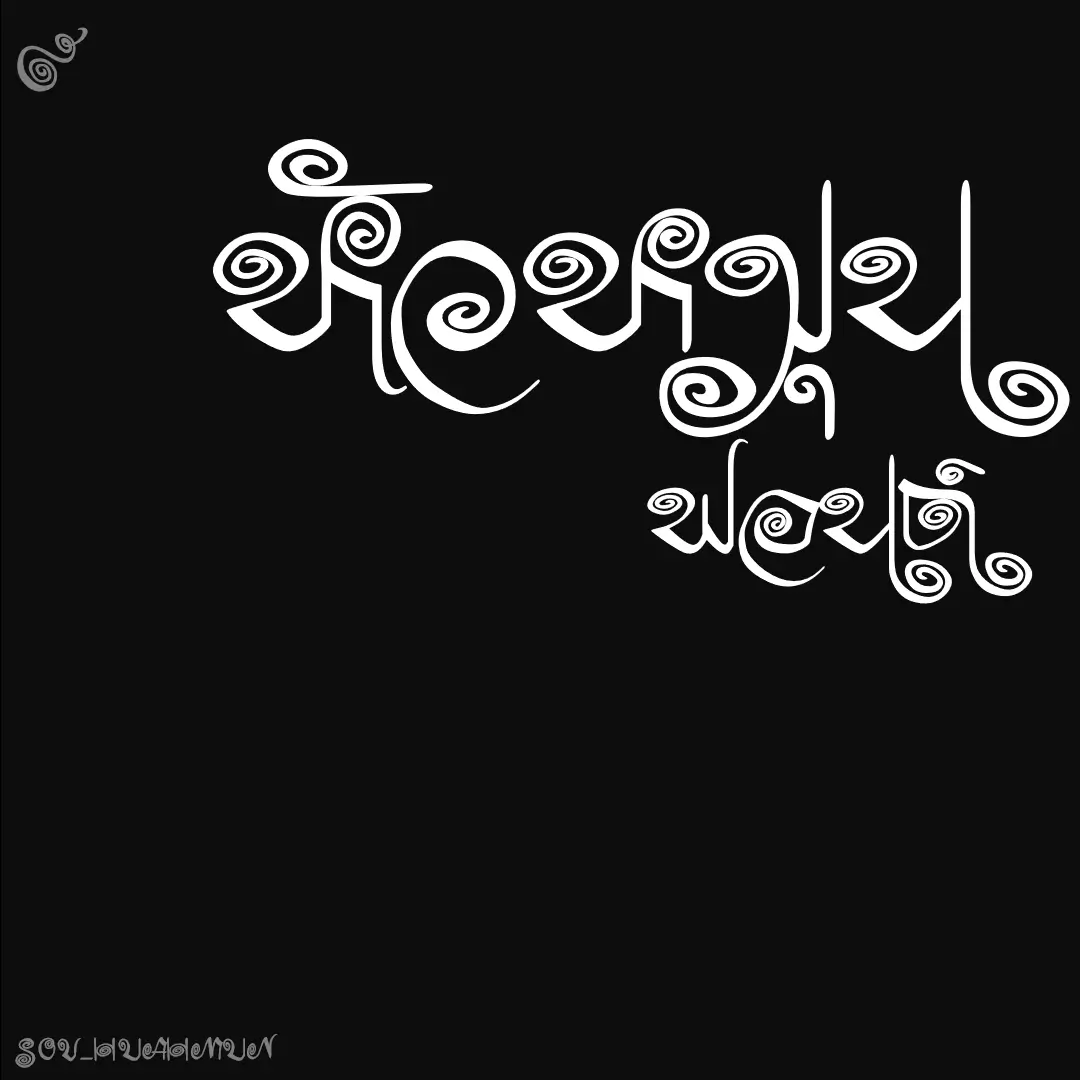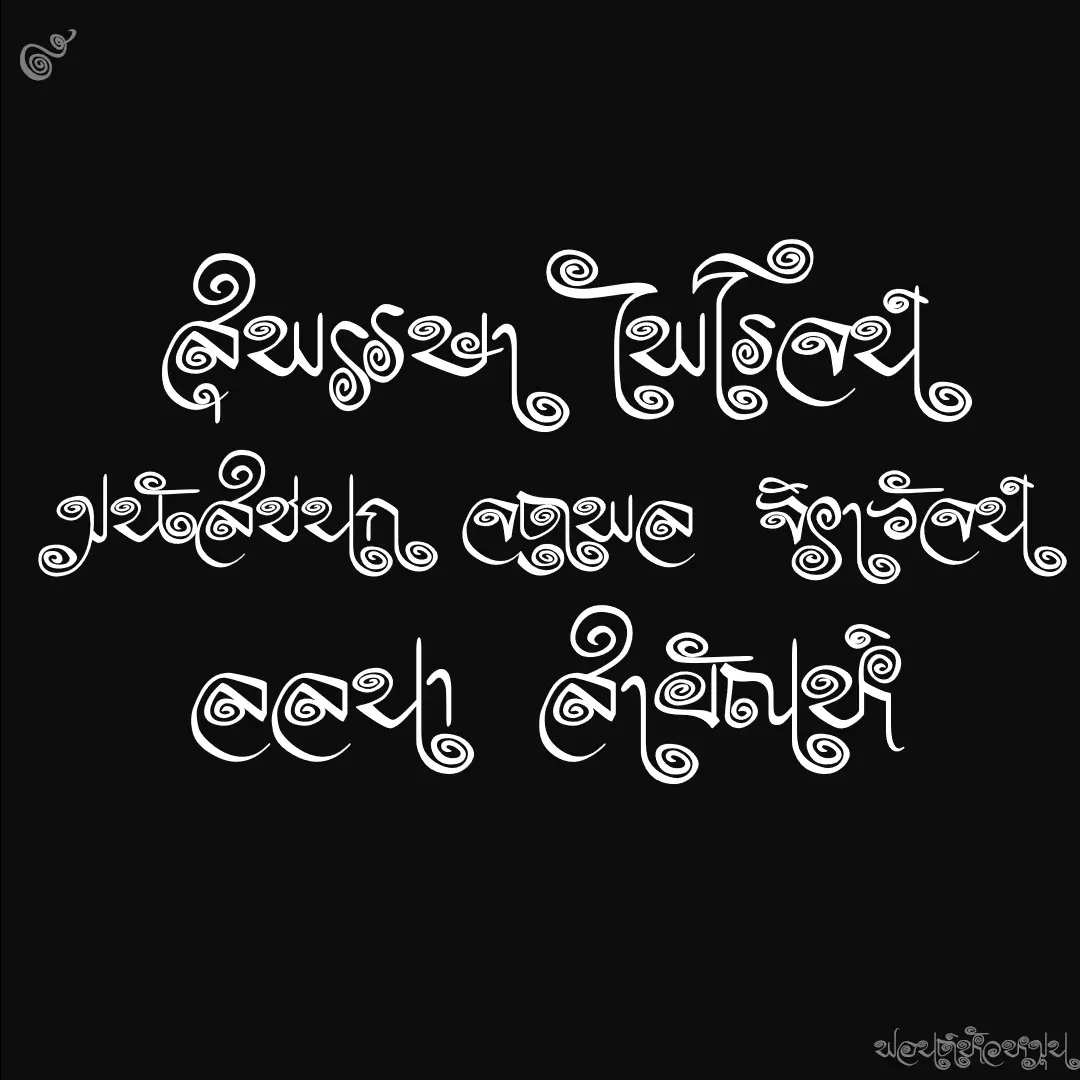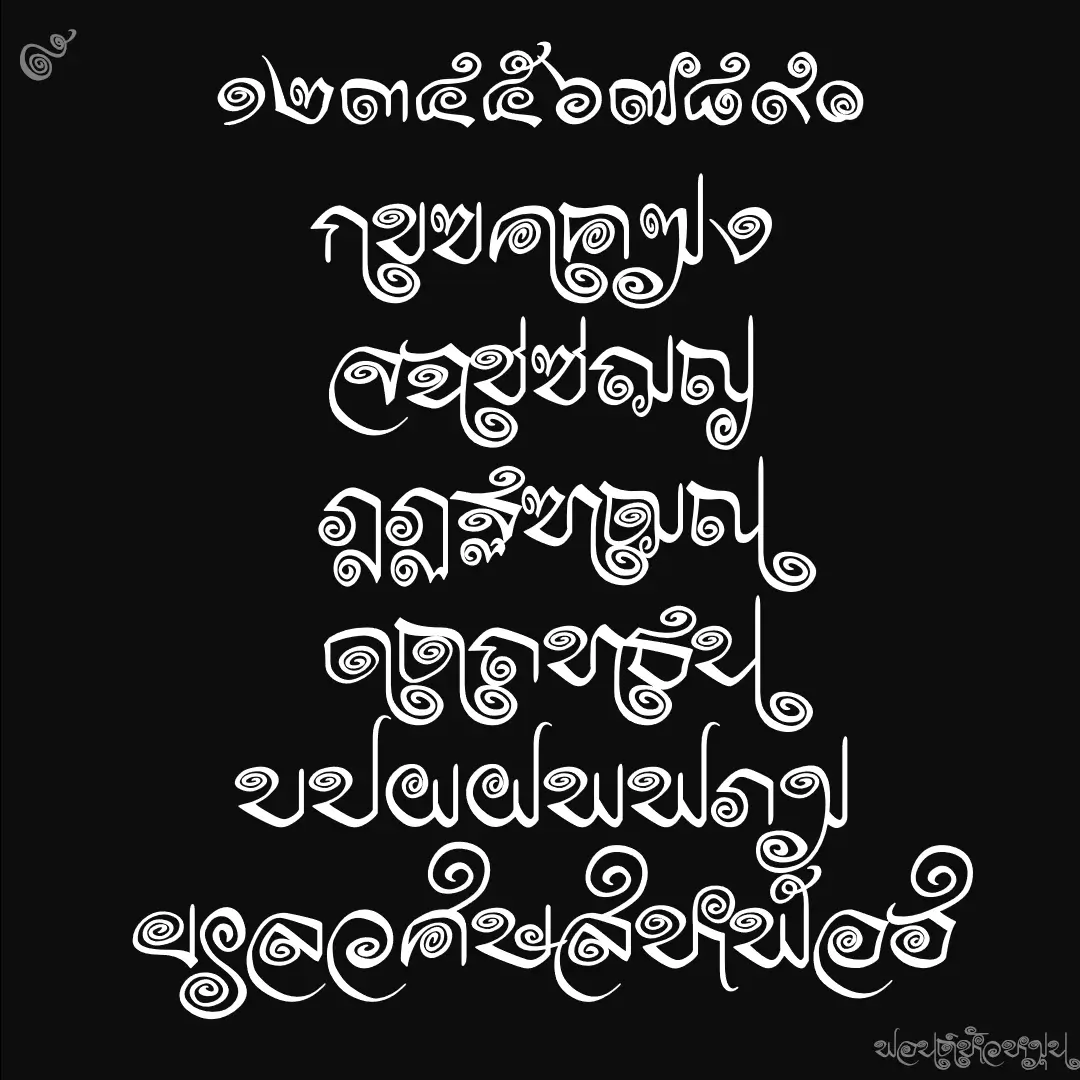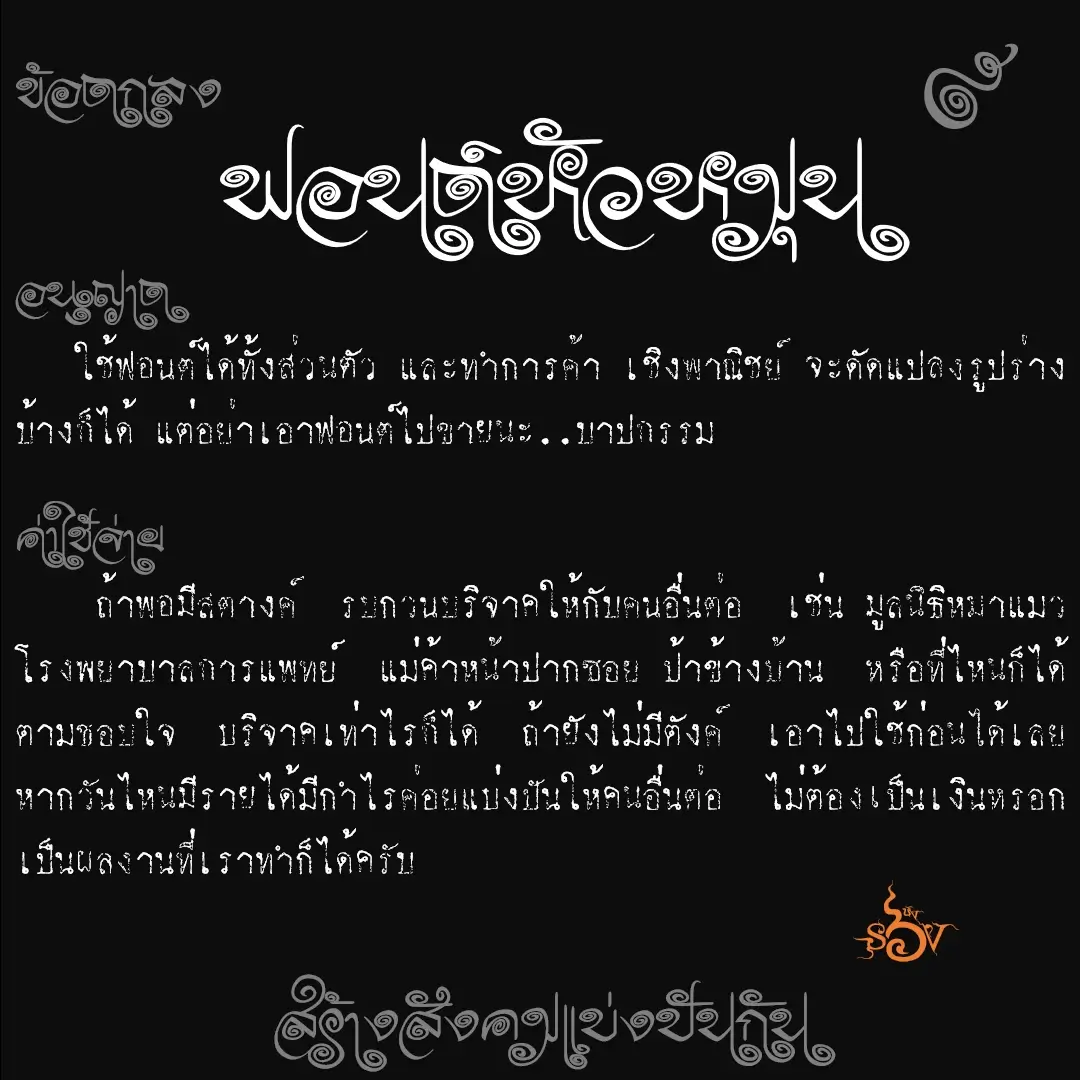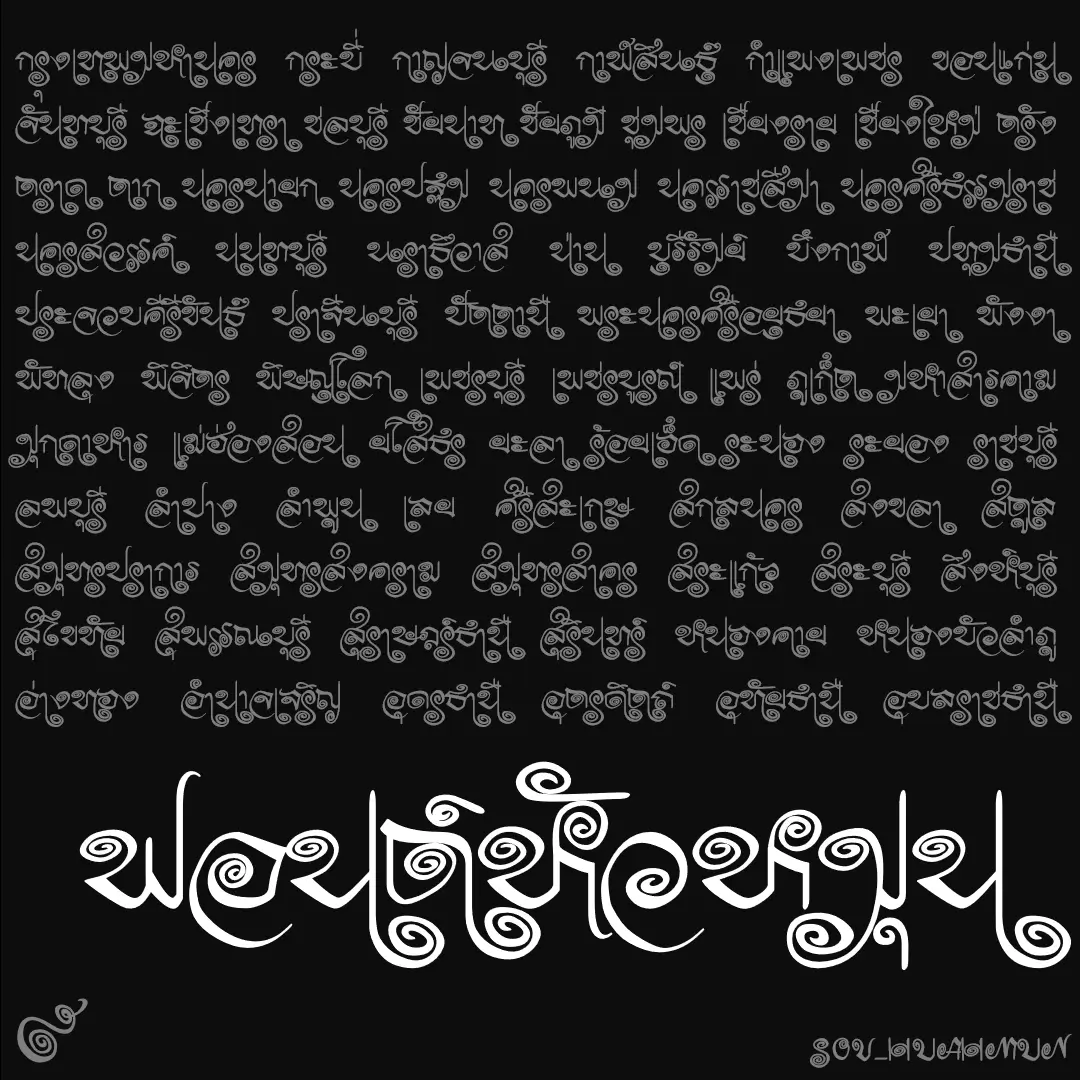
ฟอนต์หัวหมุน – ต้นทางจากนิตยสารบันเทิงปีลึก นึกๆ ตอนทำก็หัวหมุนเพราะต้องแก้ปัญหาอักษรหมุนหัวมาทับกัน
เบื้องหลังการออกแบบ : ฟอนต์ หัวหมุน
หัวหมุน (SOV_HuaHmun)